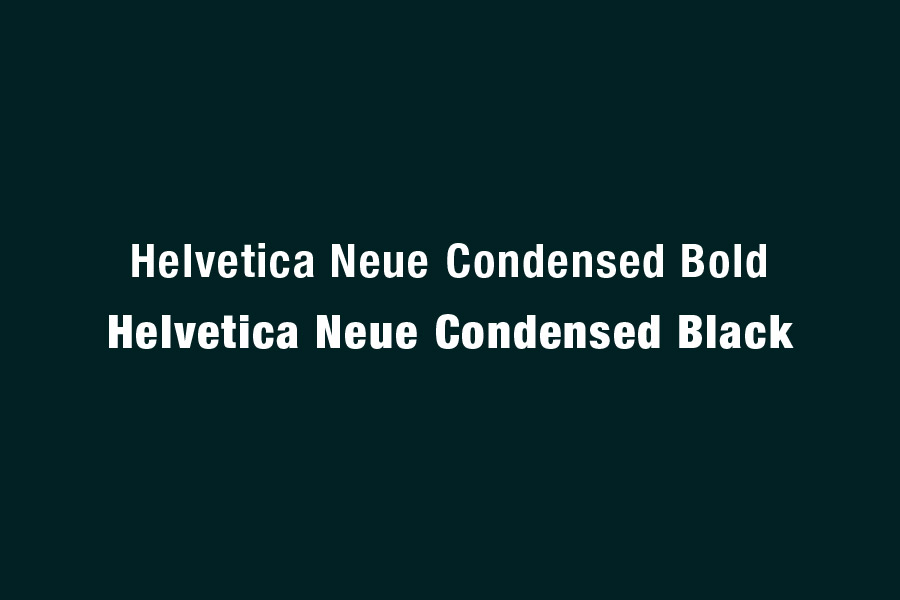
Font chữ - yếu tố quan trọng không thể thiếu trong thiết kế, góp phần tạo nên tính thẩm mỹ và sự chuyên nghiệp cho sản phẩm. Font Helvetica, với tính linh hoạt và khả năng ứng dụng cao, luôn là lựa chọn hàng đầu của nhiều nhà thiết kế. Tuy nhiên, khi sử dụng Helvetica font Việt hóa, bạn có thể gặp một số khác biệt nhỏ trong cách hiển thị các ký tự có dấu. Bài viết này sẽ giới thiệu đến bạn hai bộ Helvetica Việt hóa phổ biến, giúp bạn dễ dàng lựa chọn bộ font phù hợp nhất, mang lại sự hoàn hảo cho dự án của mình.
Bạn đang tìm kiếm một font chữ vừa ổn định, dễ sử dụng, vừa đảm bảo tính thẩm mỹ cho các dự án thiết kế? Bộ font SVN Helvetica Việt hóa chính là giải pháp hoàn hảo dành cho bạn. Với 4 kiểu cơ bản: Regular, Bold, Italic và Bold Italic, bộ font này mang đến sự đồng nhất và gọn gàng cho mọi văn bản.
Tính dễ đọc cao: Các ký tự, đặc biệt là chữ Ư và Ơ, được thiết kế tỉ mỉ, loại bỏ khoảng cách thừa khi đứng cạnh các chữ cái khác, tạo nên sự liền mạch, hài hòa cho văn bản.
Đảm bảo tính thống nhất: Bộ font chỉ gồm 4 kiểu cơ bản, giúp bạn dễ dàng duy trì sự đồng nhất trong toàn bộ thiết kế, mang đến vẻ chuyên nghiệp, tinh tế.
Ít sự lựa chọn: Do chỉ có 4 kiểu, bộ font có thể hạn chế sự sáng tạo trong các thiết kế đòi hỏi nhiều biến tấu về kiểu dáng.
Tính linh hoạt chưa cao: Bộ font chưa thực sự phù hợp với những thiết kế yêu cầu sự phá cách, đổi mới về phong cách.
Mặc dù còn một số hạn chế nhất định, bộ font chữ Helvetica Việt hóa này vẫn là lựa chọn tuyệt vời cho các tài liệu, ấn phẩm yêu cầu sự trang trọng, rõ ràng và dễ đọc.
Bộ font Helvetica Việt hóa thứ hai mang đến sự đa dạng về kiểu dáng với ba nhóm chính: Chữ đứng, chữ nghiêng và một kiểu cuối cùng được tác giả thu gọn chiều ngang giúp font có phần hẹp hơn. Sự phong phú này cho phép bạn tự do sáng tạo và điều chỉnh font chữ phù hợp với nhu cầu thiết kế.
Linh hoạt và đa dạng: Ba nhóm kiểu chữ mang đến sự linh hoạt, cho phép bạn dễ dàng thay đổi phong cách chữ trong cùng một thiết kế. Đặc biệt hữu ích cho những dự án đòi hỏi sự sáng tạo và biến tấu đa dạng.
Kích thích sáng tạo: Với nhiều lựa chọn kiểu dáng, bộ font này là công cụ tuyệt vời để bạn thỏa sức sáng tạo, tạo nên sự độc đáo và mới mẻ cho từng phần văn bản.
Khoảng cách ký tự chưa hoàn hảo: Một số ký tự như Ư và Ơ có khoảng cách hơi lớn so với các ký tự khác, dẫn đến hiện tượng chữ bị dàn trải, ảnh hưởng đến tính thẩm mỹ, đặc biệt là trong các đoạn văn bản dài.
Hạn chế khi sử dụng cho văn bản dài: Do khoảng cách ký tự không đồng đều, bộ font này có thể không phải lựa chọn tối ưu cho các văn bản dài hoặc những thiết kế yêu cầu sự đồng nhất và gọn gàng.
Như vậy, bộ Helvetica font Việt hóa thứ hai là lựa chọn phù hợp cho các dự án thiết kế đề cao tính sáng tạo và sự linh hoạt trong việc thể hiện kiểu chữ. Tuy nhiên, bạn cần cân nhắc kỹ khi sử dụng cho văn bản dài.
Việc lựa chọn giữa hai bộ Helvetica font Việt hóa này sẽ phụ thuộc vào yêu cầu và mục đích của từng dự án thiết kế. Nếu bạn cần một font chữ ổn định, dễ sử dụng và không đòi hỏi quá nhiều sự thay đổi về kiểu dáng, bộ font SVN Việt hóa sẽ là sự lựa chọn hoàn hảo. Tuy nhiên, nếu bạn cần sự đa dạng và linh hoạt trong thiết kế, đặc biệt là với các dự án sáng tạo, bộ font Helvetica Việt hóa (Ba nhóm kiểu font) sẽ đáp ứng tốt hơn.